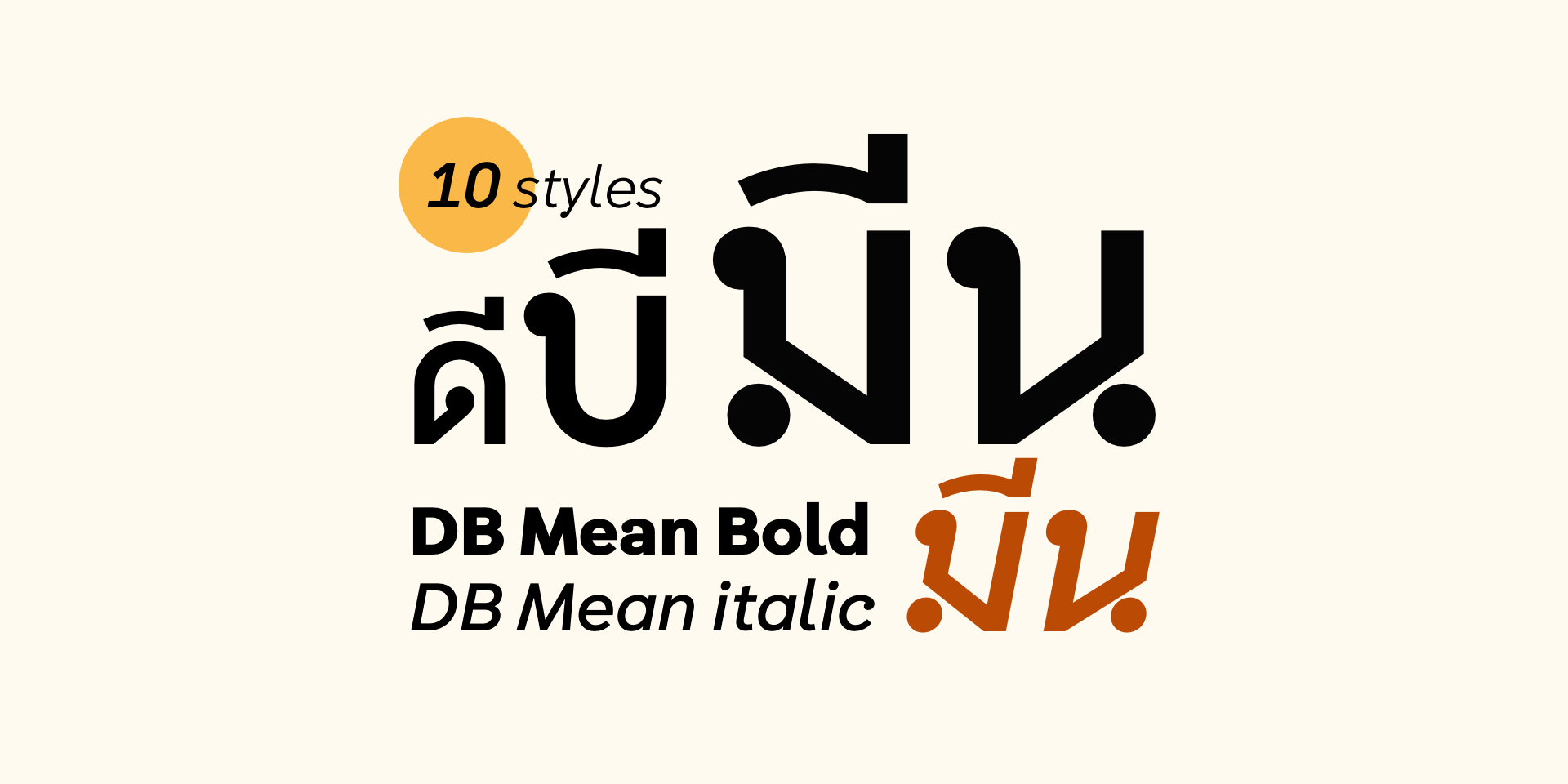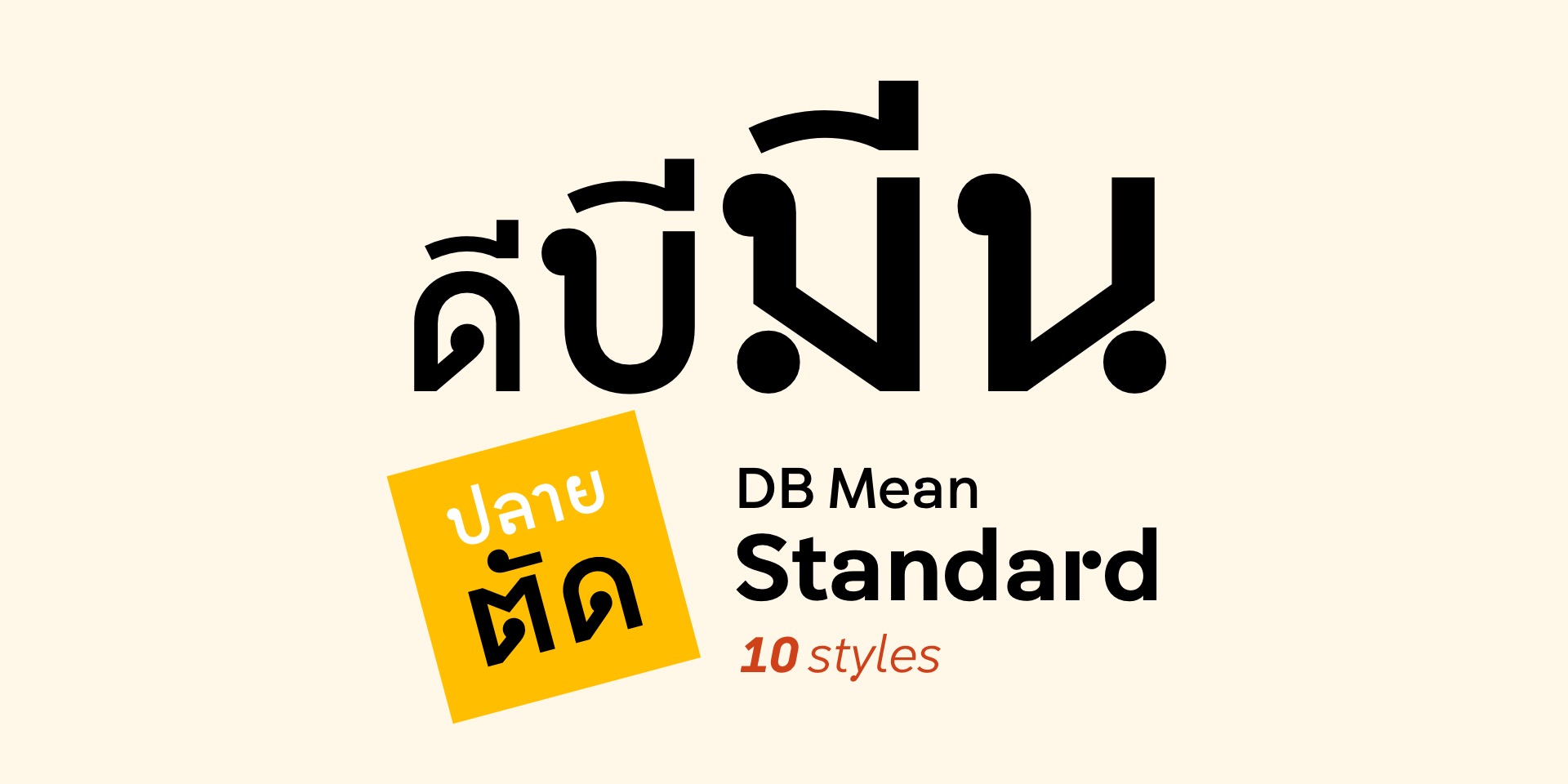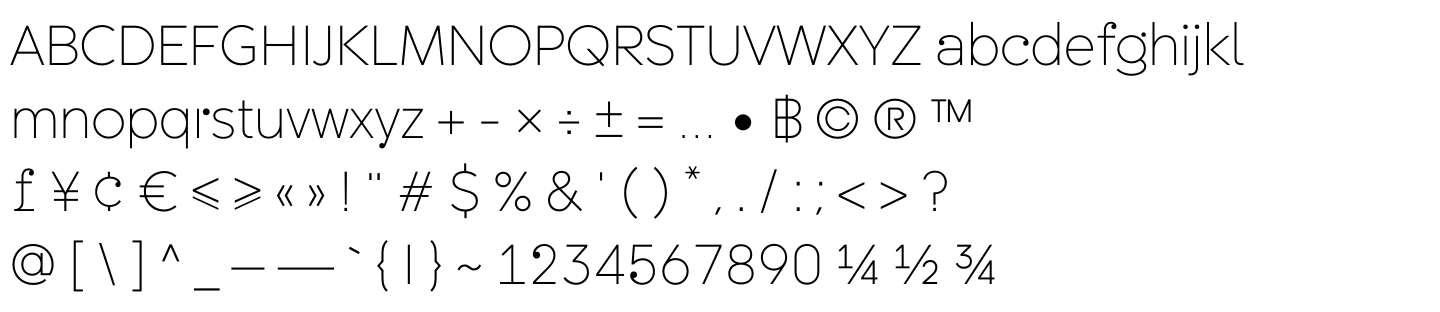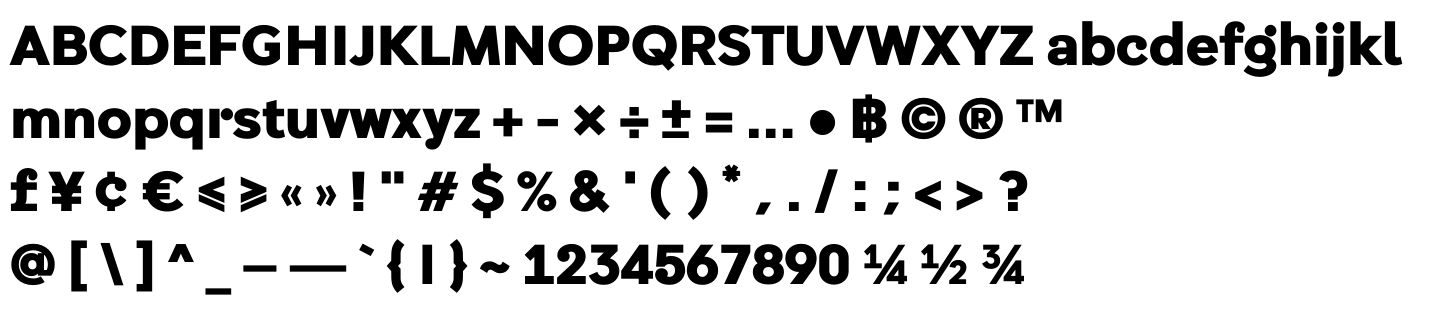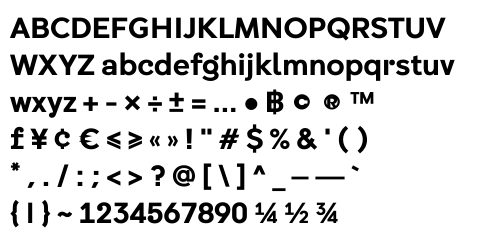
DB Mean
ดีบี มีน
- ต่อยอดมาจากฟอนต์ดีสเพลย์ DB Mixtura
- ด้วยการเติมหัวอักษรให้ครบทุกตัวพร้อมจูนสัดส่วนใหม่
- ปรับ ด ต ธ ร ทรงดีสเพลย์ของ DB Mixtura ให้เป็นทรงเท็กซ์
- เกิดเป็นฟอนต์ไทยแนวใหม่
- อยู่กึ่งกลาง (mean) ระหว่างตัวพื้นกับตัวพาดหัว
- ทั้งอ่านง่ายใกล้เคียงฟอนต์ตัวพื้นไทยมาตรฐาน
- และดูสดใหม่แบบฟอนต์ตัวพาดหัวไทยร่วมสมัย
- จะใช้ DB Mean เป็นตัวพาดหัวก็ได้ เป็นตัวพื้นก็ดี
- ถ้าใช้ DB Mean เป็นตัวพื้นร่วมกับตัวพาดหัว DB Mixtura ยิ่งดี!